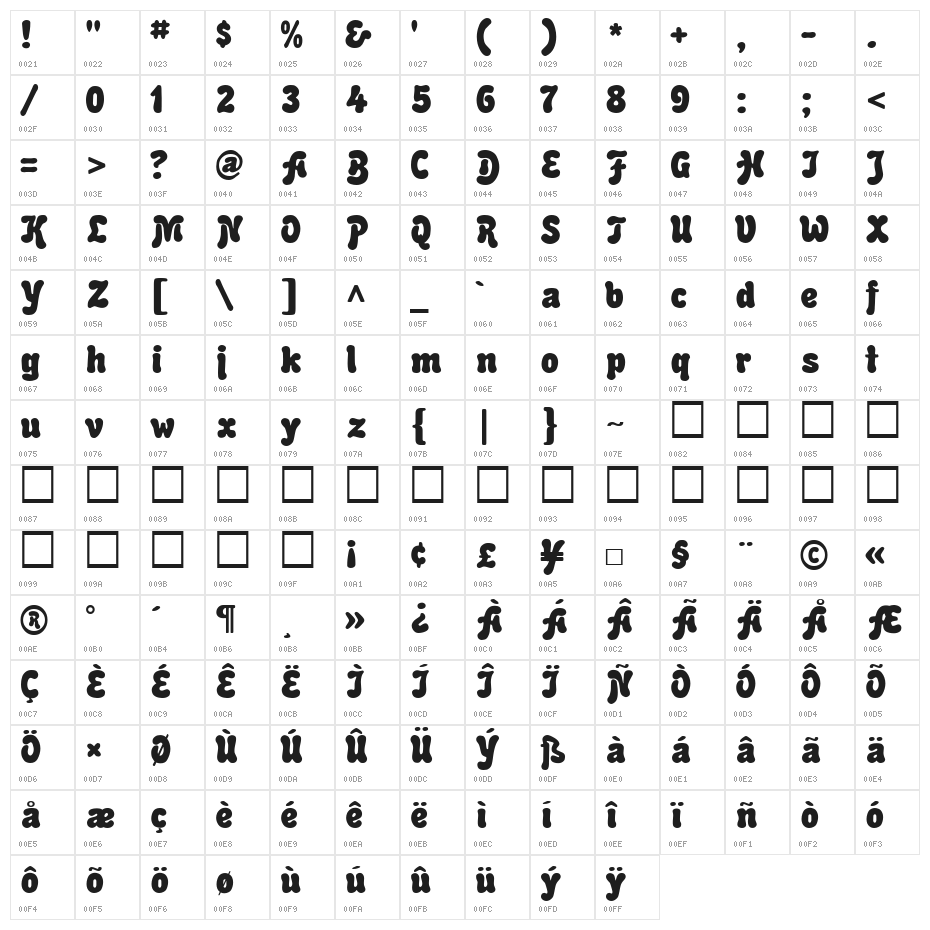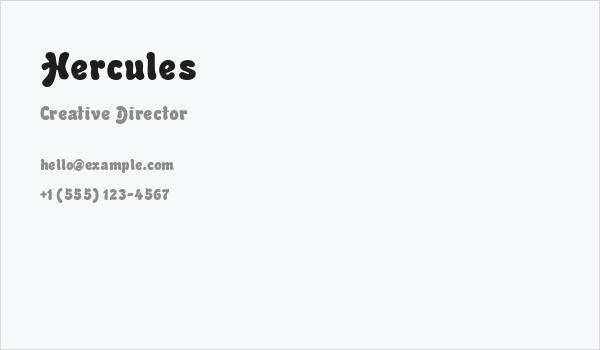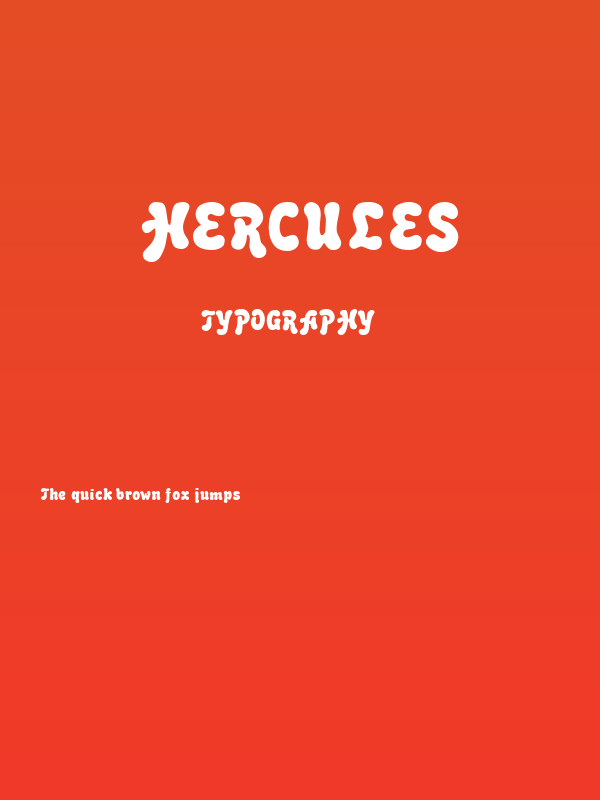
Hercules Font
| Stil general | Playful, Bold, Decorative |
| Proiecte propuse | Ideal for children's books, playful branding, posters, and creative advertising. |